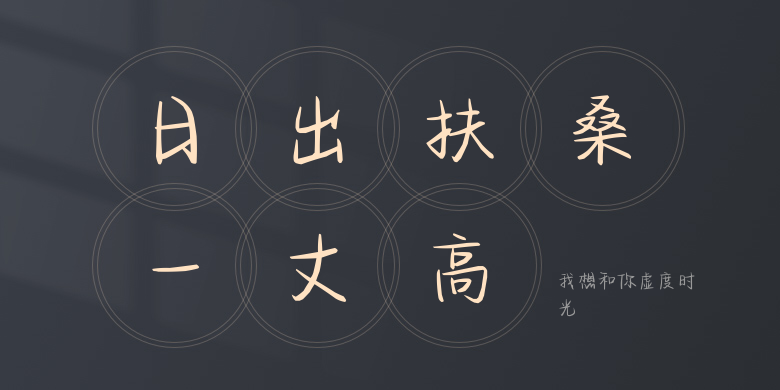
我想和你虚度时光
我想和你虚度时光,这款字体结构工整、笔画清晰,兼顾美观与易读性,适用于标题、正文、海报、包装、LOGO 等多种场景。字形优雅稳定,风格百搭耐看,适配日常排版与创意设计,让文字呈现更舒适、更具质感。我想和你虚度时光一笔一画,皆是细节,以均衡的比例、流畅的线条打造舒适视觉体验,字形端正大气,风格简约现代。无论是商业设计、品牌宣传还是日常排版,都能轻松驾驭,让文字更有格调与力量。我想和你虚度时光字体下载。